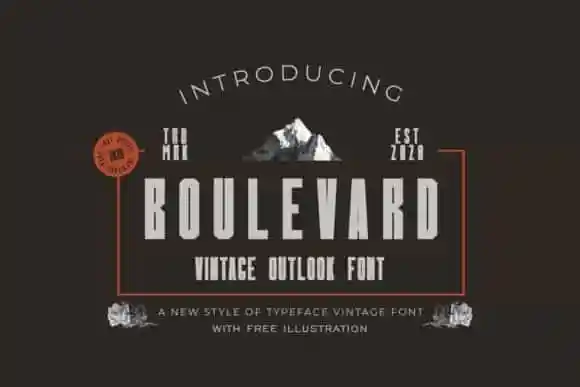
A fonte Boulevard Display Font é uma opção criativa para projetos que precisam de um ar vintage e moderno ao mesmo tempo. Especialmente adequada para logomarcas, capas de livros, identidades corporativas, revistas ou qualquer outro projeto em que você deseje destacar a elegância e personalidade de seu design. Desenvolvida por JujunGag na 99designs, esta fonte apresenta um estilo vintage mas também traz uma sensação leve e despojada através dos ilustrações que ela incorpora. Com letras maiúsculas completas, números e uma grande variedade de pontuação, é perfeita para qualquer tipo de projeto gráfico, tornando-a uma excelente escolha para designers em busca de um ar de personalidade ao criar seus trabalhos.